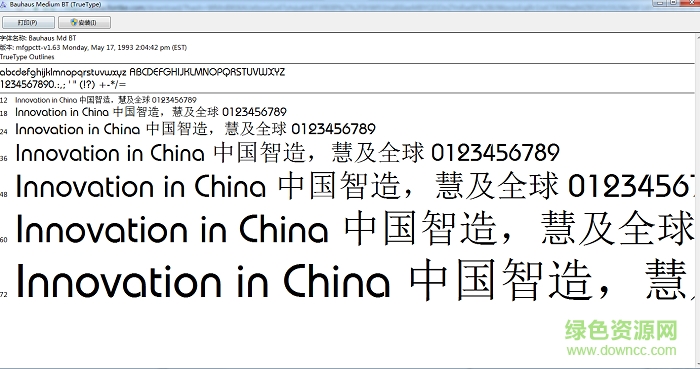
bauhaus md bt普通常規(guī)體/粗體
bauhaus md bt字體是綠色資源網(wǎng)各位朋友搜集的英文字體,包含了常規(guī)體和粗體兩款,字體構(gòu)造精美,線(xiàn)條流暢不累贅,極具視覺(jué)美感,簡(jiǎn)潔易認(rèn),需要的朋友快來(lái)下載吧!
bauhaus md bt常規(guī)體